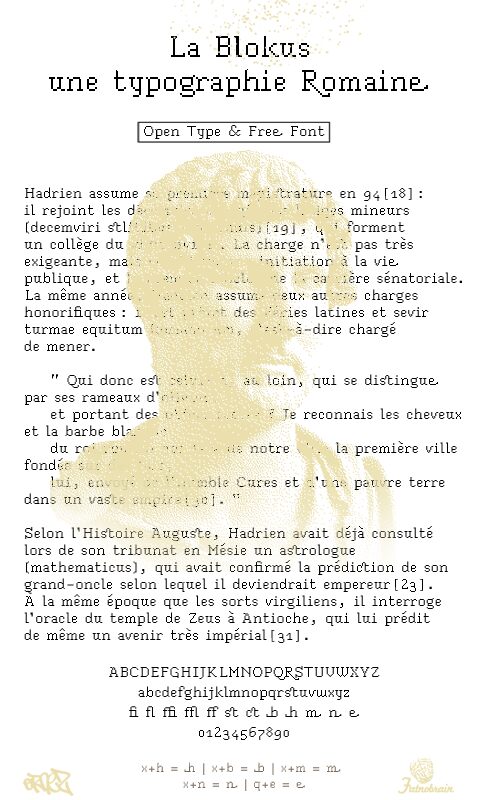
Blokus to darmowy font ekranowy o charakterze pikselowym, zbudowany z kwadratowych bloków wyrównanych do siatki. Jego litery łączą schodkowe krzywe z nagłymi przerwami i ściętymi narożnikami, przywodząc na myśl niskorozdzielczą grafikę z automatów do gier. Niejednorodne sylwetki sprawiają, że sztywna konstrukcja wydaje się niespokojna i celowo nieregularna.
Grafika gier to jego najbardziej oczywiste zastosowanie, zwłaszcza ekrany tytułowe czerpiące z retro cyfrowej estetyki, a ta sama blokowa budowa pasuje również do plakatów muzyki elektronicznej i gadżetów na wydarzenia technologiczne. W brandingu produktów potrafi zamienić nazwy w kafelkowe emblematy.
La Blokus to krój pisma pomyślany jako adaptacja antykwy do składu ekranowego.
Opracowano ligatury oraz zaprojektowano litery wejściowe i wyjściowe.
Na ekranie przy 16 punktach La Blokus jest optymalny.
Do druku tekst można składać w rozmiarach od 5 punktów.